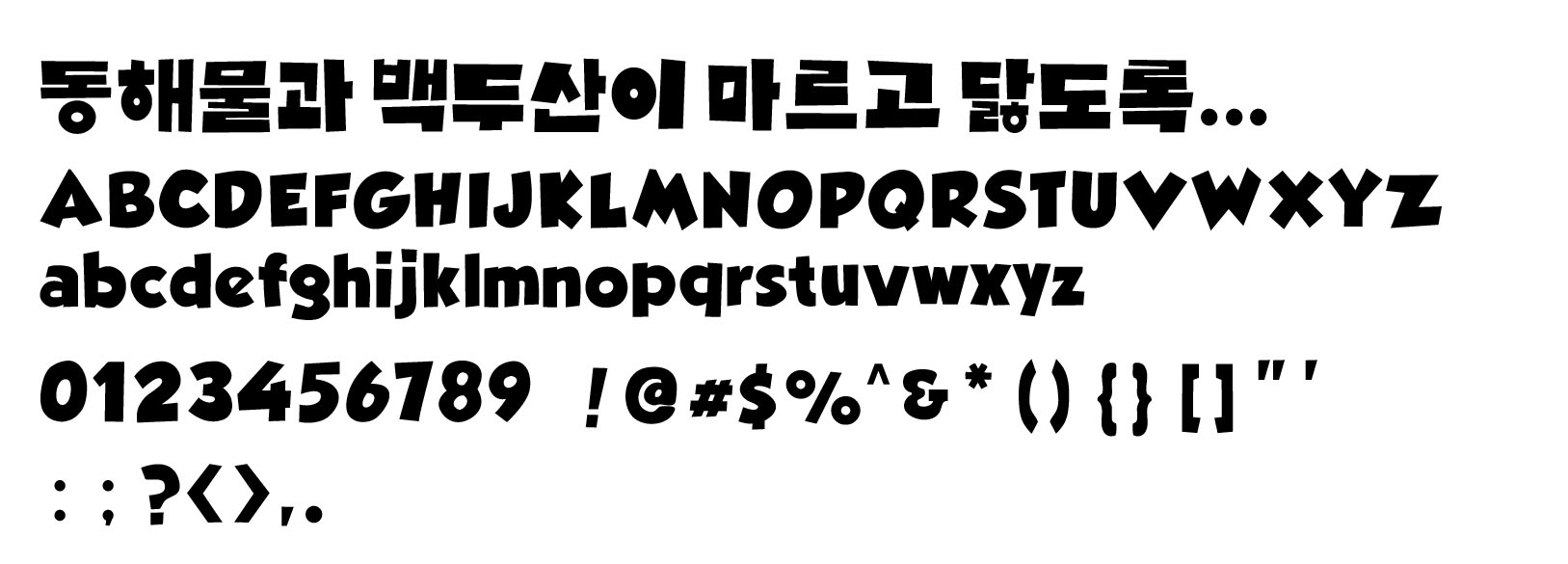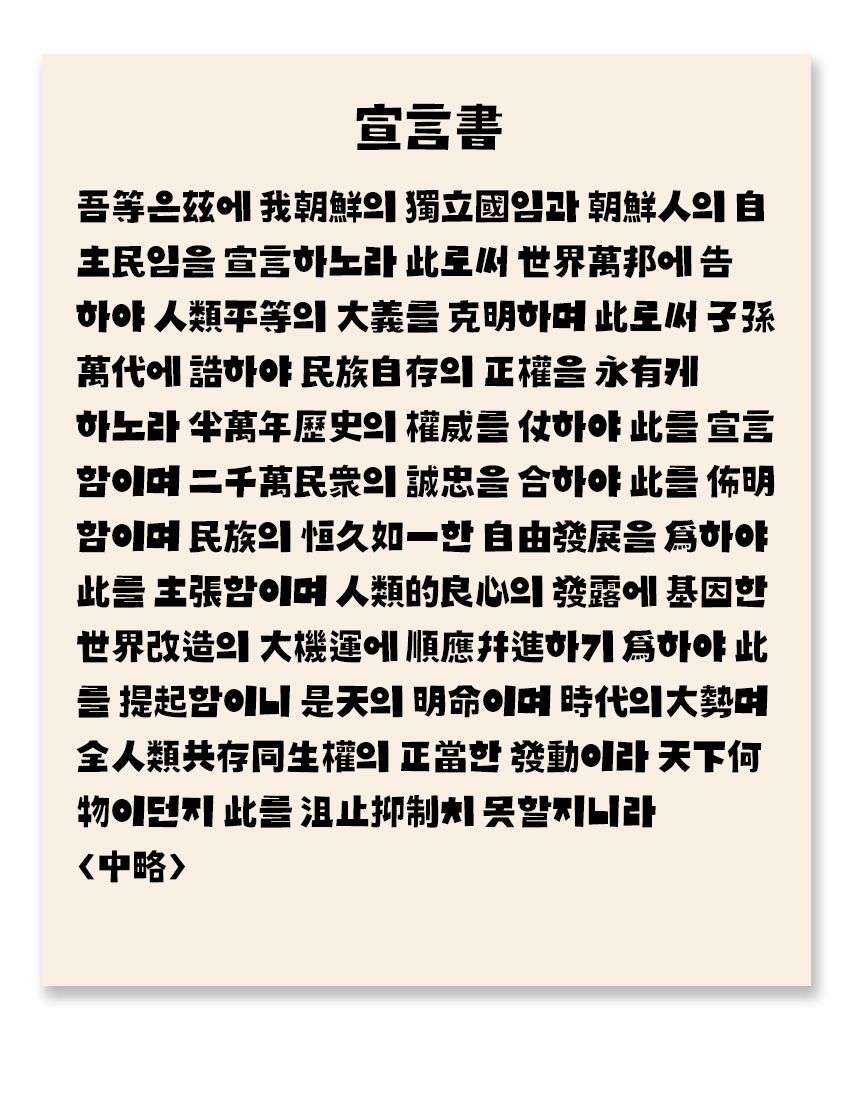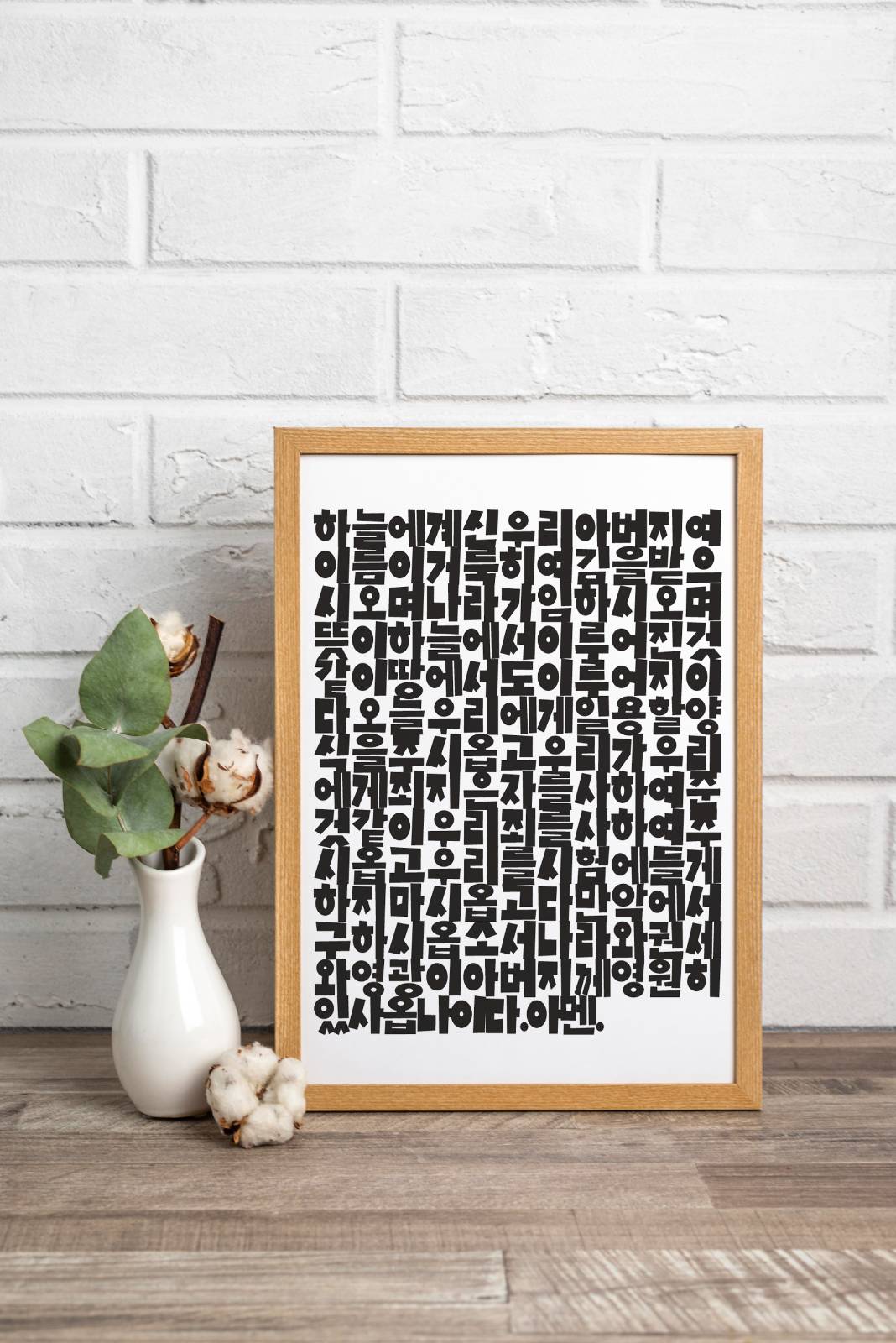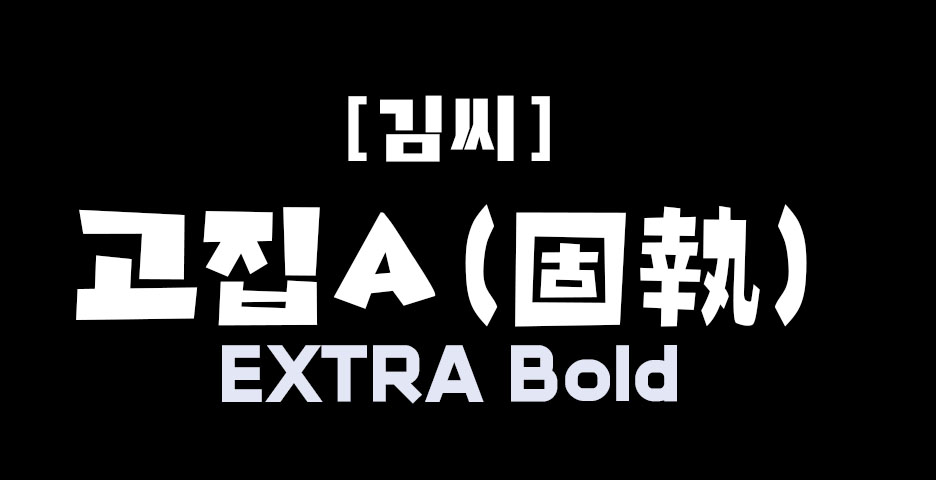
[김씨]고집체는 두꺼운 굵기의 제목용 폰트입니다.
강한 주목성을 필요로 하는 포스터, 표지 등 디스플레이 용도에 적당하도록 디자인되었습니다.
●● 폰트구성
1. 한글11,172자+한자4,888자 버전 1종
3. 영문 52자(대,소문자)
4. 숫자 10자
5.기본약물 32자